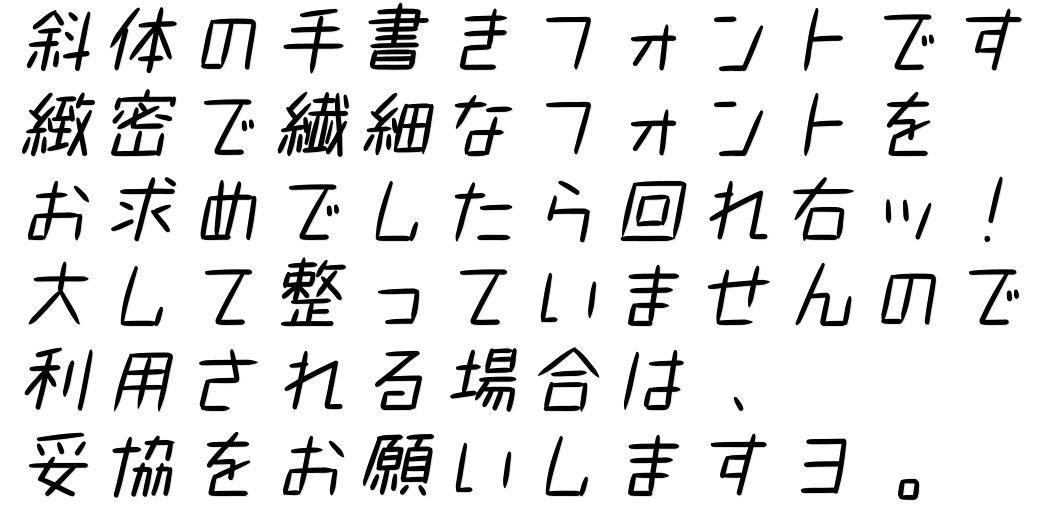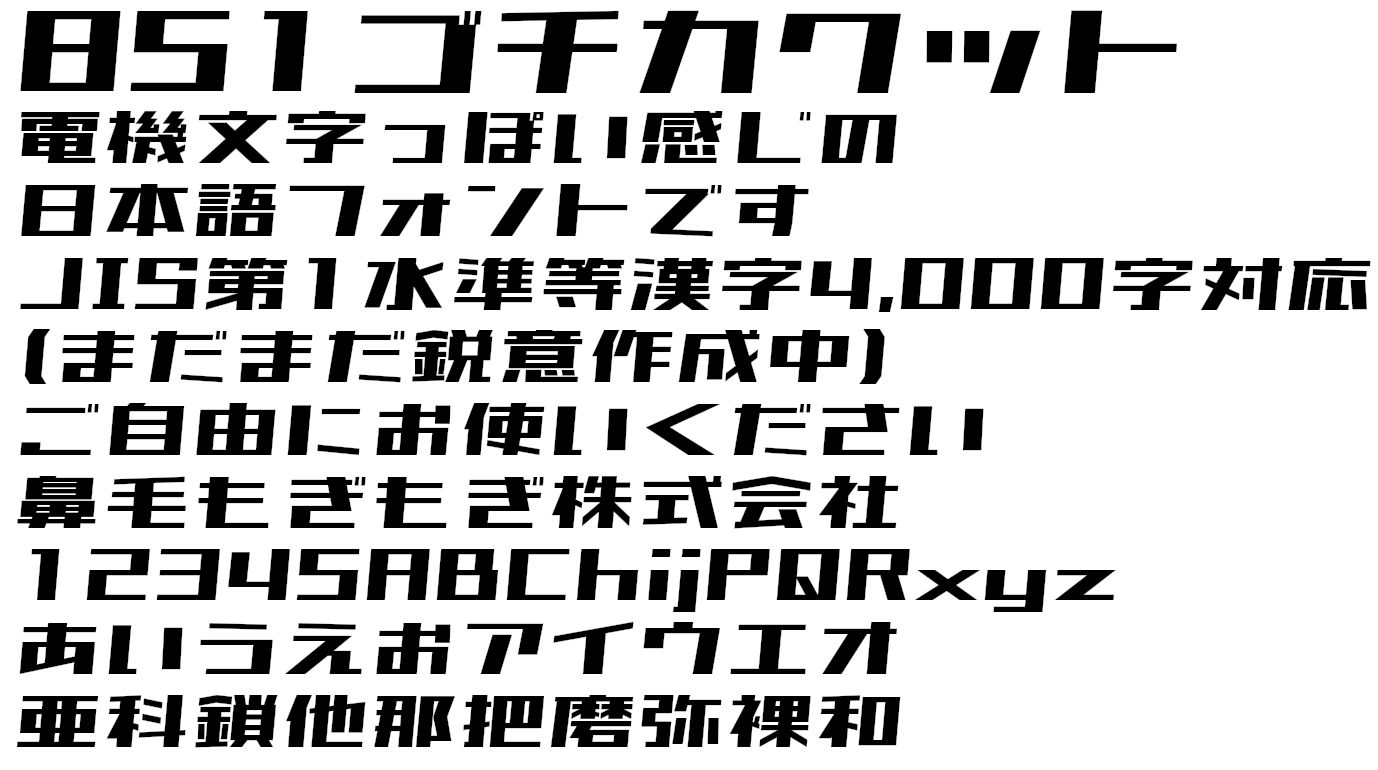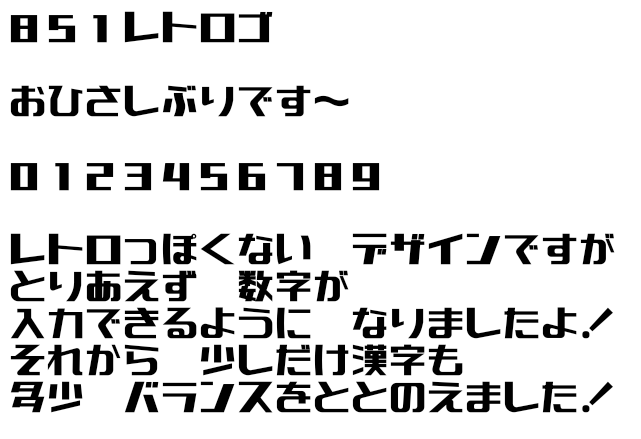
851可商用日文字体完整版
851系列日文字体由日本设计师 8:51:22 pm 设计,作者在官网以免商授权方式发布,支持部分简体中文。目前851系列字体共7款,后续如有迭代或新字发布,素材君会同步在这里更新。
851手書き雑フォント
一款手写风格日文字体,和我们日常使用圆珠笔写出来的效果很像。这款字体虽然是日文字体,但其中包含的中文简体字和繁体字也是比较完整的。
851マカポップ
851チカラヨワク
851テガキカクット
851チカラヅヨク
851ゴチカクット
一款充满锐利感的刚性字体,笔画和众多现代美术体相似,延续了横细竖粗的风格,所以非常适合应用于各种海报、banner 的标题处。该字体目前有4000多个汉字字符,因此在输入简体中文时,可能会出现缺字的情况。
851レトロゴ